Die 21 besten Designer-Schriftarten 2023 (kostenlos und Premium)
Veröffentlicht: 2023-05-23Fällt es Ihnen schwer, die richtige Schriftart für Ihre Designprojekte zu finden? Sind Sie es leid, die gleichen alten Schriftarten zu verwenden und möchten neue Optionen ausprobieren?
Suchen Sie nicht weiter! In diesem Blogbeitrag haben wir eine Liste der 21 besten Designer-Schriftarten zusammengestellt, die Ihre Designs auf die nächste Stufe heben. Diese Schriftarten wurden sorgfältig zusammengestellt, um den unterschiedlichen Designanforderungen gerecht zu werden, von minimalistisch bis dramatisch, modern bis vintage.
Wussten Sie, dass die Wahl der richtigen Schriftart die Lesbarkeit und Gesamtästhetik Ihres Designs drastisch verbessern kann? Laut einer Studie des MIT können Menschen schneller lesen und mehr Informationen behalten, wenn die Typografie gut lesbar und ästhetisch ansprechend ist. Bei so vielen verfügbaren Schriftarten kann es überwältigend sein, die richtige auszuwählen. Deshalb haben wir die harte Arbeit für Sie erledigt und die besten Optionen eingegrenzt.
In diesem Artikel stellen wir jede Schriftart mit einer kurzen Beschreibung, ihren einzigartigen Funktionen und Beispielen für ihre Verwendung vor.
Lassen Sie uns also ohne weitere Umschweife in die 21 besten Designer-Schriftarten eintauchen, die jeder Grafikdesigner kennen sollte.
Beste Premium-Designer-Schriftarten
In diesem Abschnitt haben wir eine Liste der besten Designer-Premium-Schriftarten zusammengestellt, die Ihre Designprojekte mit Sicherheit aufwerten werden. Werfen Sie einen Blick darauf und entdecken Sie die perfekte Schriftart für Ihr nächstes Projekt!
Fällige Gutschrift
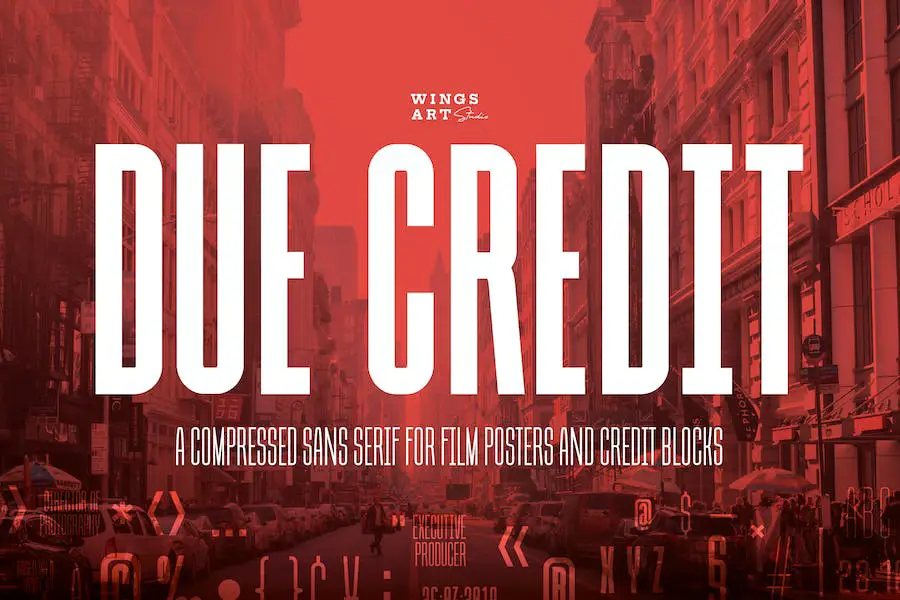
Due Credit ist eine vielseitige Schriftart, die Ihren Designs einen Hauch von Klasse verleihen kann. Es ist in verschiedenen Stärken erhältlich und eignet sich daher ideal für die Erstellung auffälliger Titel und Zitate. Darüber hinaus verfügt es sogar über einen Stil, der von Horror-Genres inspiriert ist und sich perfekt für Halloween-Projekte eignet.
Diese Schriftart wurde speziell für Adobe-Benutzer entwickelt und kann zum Erstellen atemberaubender Typografie in verschiedenen Anwendungen verwendet werden.
Die Auswahl an Stilen und Gewichten stellt sicher, dass Designer die perfekte Option auswählen können, die zur Ästhetik ihres Projekts passt. Die klaren Linien und eleganten Kurven der Schriftart machen sie zu einer ausgezeichneten Wahl für diejenigen, die ihrer Arbeit ein professionelles und elegantes Aussehen verleihen möchten.
Wege
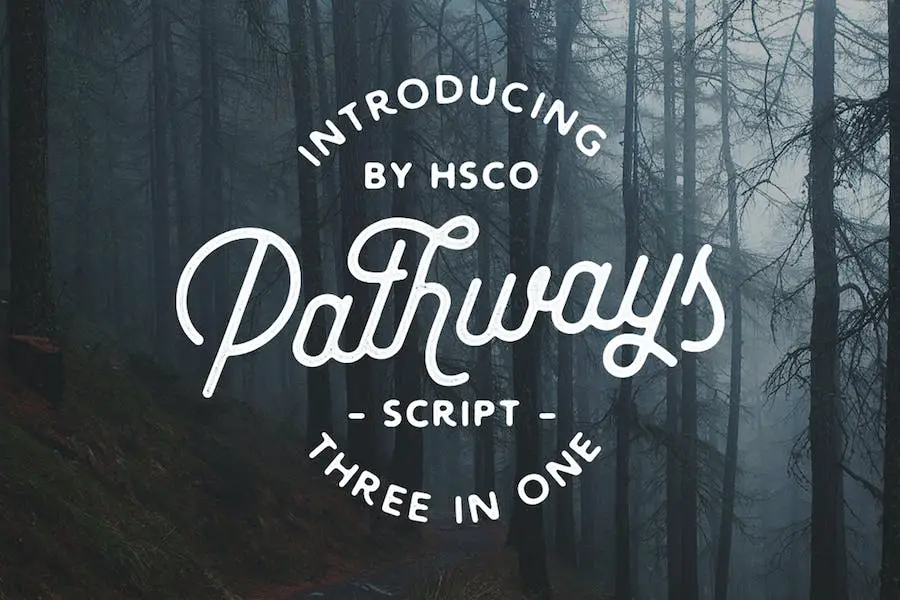
Pathways ist eine vielseitige Schriftart, die in drei verschiedenen Stilen erhältlich ist: kreisförmige Striche, rechteckige Striche und eine grobe Version für eine gedruckte Ästhetik.
Diese Schriftart wurde speziell für Logo- und Etikettendesigner entwickelt und bietet viele alternative Zeichen und Ligaturen, was sie zu einem hervorragenden Werkzeug für Designer macht, die das Design ihrer Projekte verbessern möchten.
Das klare und vielseitige Design von Pathways ist perfekt für alle, die nach Designer-Schriftarten für Canva suchen. Diese Schreibschrift verfügt über einzigartige Funktionen wie alternative Zeichen und Ligaturen, die sie von anderen verfügbaren Schriftarten abheben.
Fallen
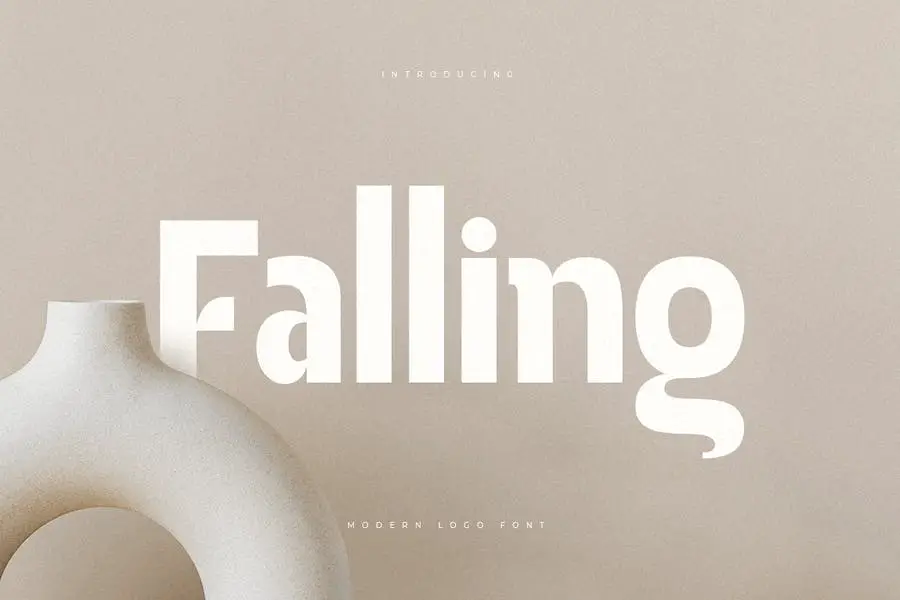
Falling ist eine moderne Schriftart, die einzigartige Branding-Lösungen bietet. Diese Schriftart wurde speziell mit zusätzlichen Ligaturen in einer einzigartigen Form erstellt, die Ihrer Marke einen Mehrwert verleihen kann.
Falling ist ein Muss für jeden, der nach Designer-Schriftarten für Figma sucht. Die zusätzlichen Ligaturen und die einzigartige Form helfen dabei, jedes Designprojekt auf die nächste Stufe zu heben. Wenn Sie Ihrer Marke einen Mehrwert verleihen und gleichzeitig mit den neuesten Designtrends Schritt halten möchten, ist Falling die perfekte Schriftart für Sie.
Stadtrundfahrt
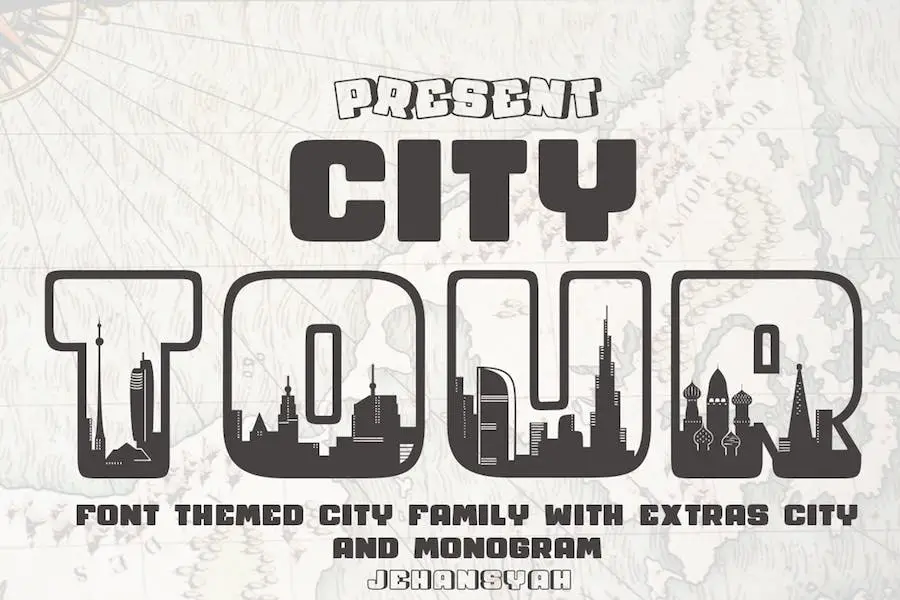
City Tour ist eine einzigartige Schriftart, die verschiedene Schriftarten und Designelemente kombiniert, um eine herausragende alphabetische Darstellung verschiedener Länder zu schaffen. Ziel ist es, Designern die Essenz jedes Landes näherzubringen und zwei Werke in einer Form zu schaffen, die Sie „Wow“ sagen lassen.
Die Schriftfamilie umfasst zehn Zeichenschriften, Extras, Dingbats sowie City TTF- und OTF-Dateien, die einfach als ZIP-Dateien heruntergeladen werden können.
Mit der City Tour-Schriftfamilie können Sie alles nach Ihren Bedürfnissen nutzen, auch die verschiedenen Dateien und Zeichen. Mit Designer-Schriftarten können Sie atemberaubende Designs für Instagram oder jede andere Plattform erstellen.
Meta-Link
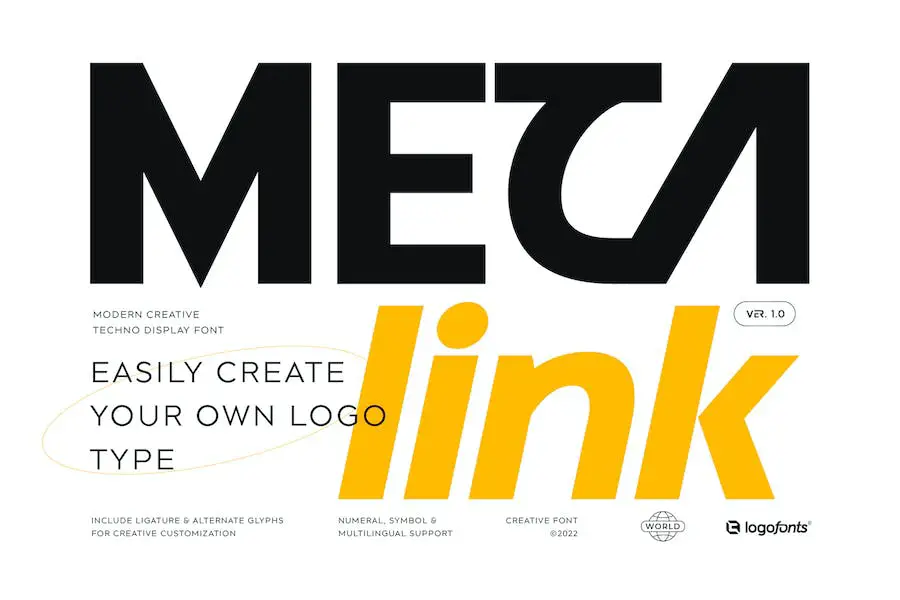
Meta Link ist eine Sans Serif, die die elegante Ästhetik zukünftiger Technologie und Sportarten verkörpern soll. Es eignet sich perfekt zum Erstellen von Logos, Postern, Schlagzeilen, Webdesigns, Magazinen, Verpackungen und Briefpapier.
Diese Schriftart bietet vier Strichstärkenoptionen mit Kursivschrift sowie eine Open-Type-Funktion, die den Zugriff auf eine große Auswahl einzigartiger alternativer Buchstaben und zahlreicher Ligaturen ermöglicht und so die Anpassung Ihrer Designs erleichtert.
Wenn Sie nach Designer-Markenschriftarten suchen, die Ihre Projekte aufwerten, dann sollte Meta Link auf Ihrer Liste stehen. Sie hat eine ausgesprochen futuristische Anmutung, die sie von anderen Schriftarten unterscheidet und Ihren Designs einen modernen Touch verleiht. Dank der vielseitigen Gewichts- und Stiloptionen können Sie eine Vielzahl von Designs kreieren, die auf Ihre Bedürfnisse zugeschnitten sind.
Die Aquabella
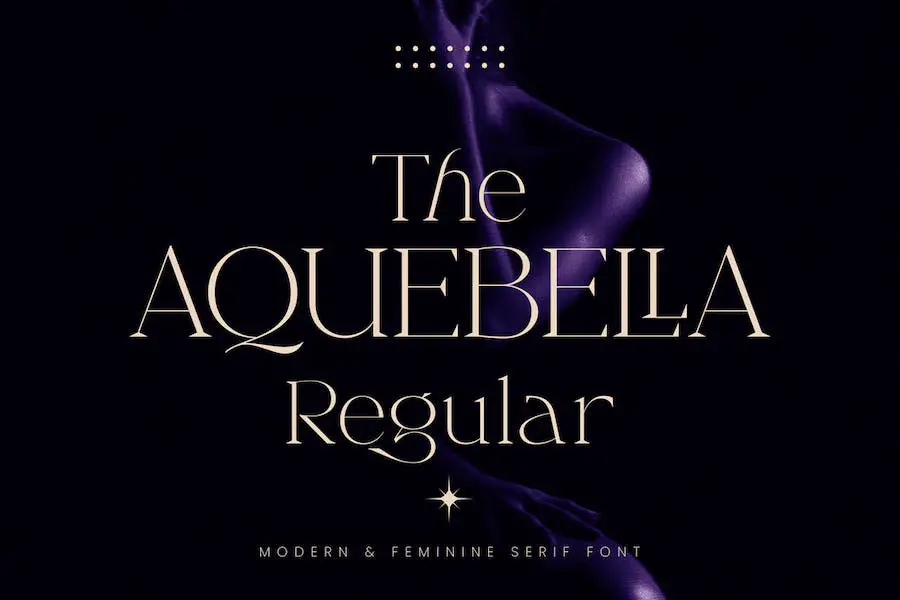
Die Schriftart Aquabella ist eine Serifenschrift, die Grafikdesignern einen einzigartigen und eleganten Stil bietet. Die Schriftart wurde entwickelt, um der Herausforderung gerecht zu werden, eine Serifenschrift zu finden, die sowohl anspruchsvoll als auch einzigartig ist.
Wenn Sie nach einer neuen und einzigartigen Serifenschrift suchen, um Ihre Designs aufzuwerten, ist The Aquabella eine Überlegung wert. Ihr eleganter Stil und ihre Lesbarkeit machen sie zu einer herausragenden Wahl unter den Designerschriften für Fotografen.
Loistave
Loistave ist eine atemberaubende zweiseitige Serifenschrift, die Raffinesse und Modernismus ausstrahlt. Mit seinen sanften Kurven und dem symmetrischen Design ist es die perfekte Wahl für jedes Mode-Branding oder redaktionelle Projekt. Diese Schriftart besitzt eine zarte Eleganz, die jedes Bild zum Leben erwecken kann.
Insgesamt ist Loistave eine Bildschrift der Spitzenklasse, die sowohl Stil als auch Funktionalität bietet. Die sanften Kurven und ausgewogenen Serifen bringen Ihre Designs auf die nächste Ebene und machen diese Schriftart zu einem Muss für jeden Designer.
Designer-Schriftartenpaket
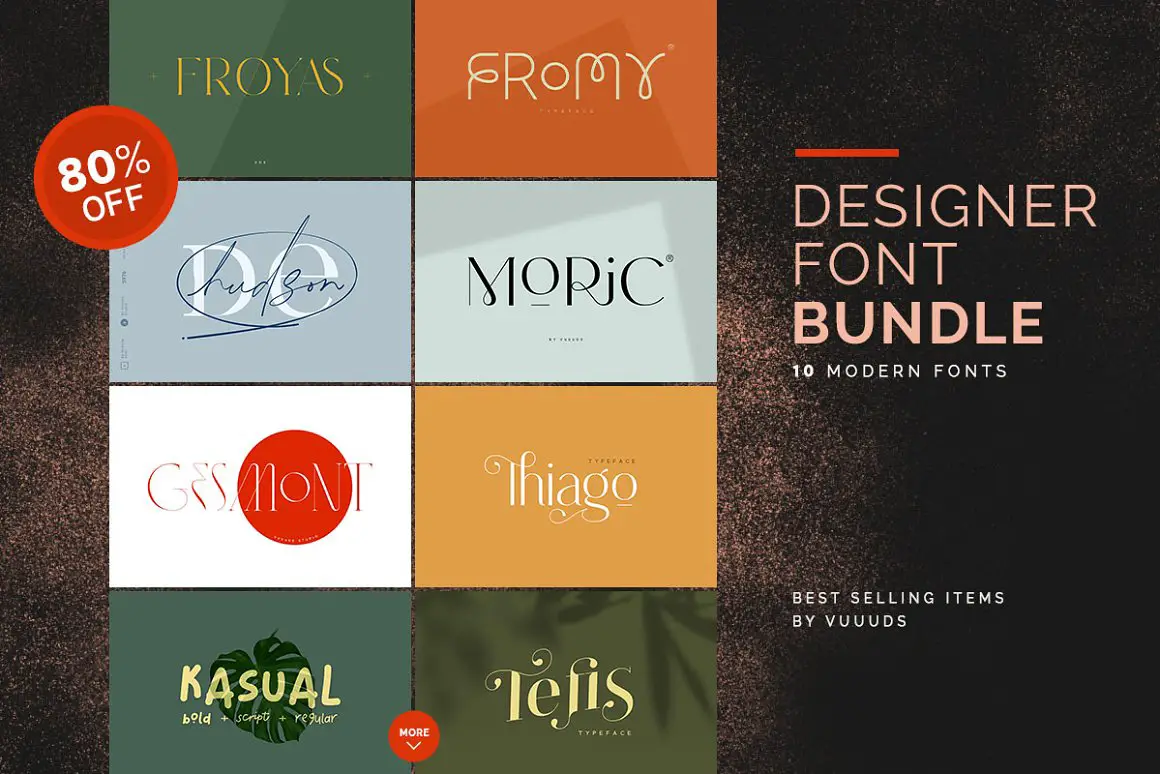
Das Designer Font Bundle ist ein Muss für jeden Grafikdesigner, der das Design seiner Projekte verbessern möchte. Dieses Paket geht über reine Schriftarten im Serifenstil hinaus und umfasst moderne Skriptschriftarten, sodass Sie mehr Optionen zum Auswählen und Experimentieren haben.
Wenn Sie Ihre Designprojekte auf die nächste Stufe heben möchten, ist das Designer Font Bundle eine ausgezeichnete Investition.
Mit der vielseitigen Auswahl an Schriftarten und der benutzerfreundlichen Oberfläche können Sie im Handumdrehen atemberaubende Designs erstellen. Und mit der Möglichkeit, Google Designer-Schriftarten zu verwenden, stehen Ihnen noch mehr Inspirationen zur Verfügung.
Minimalistisches Schriftartenpaket
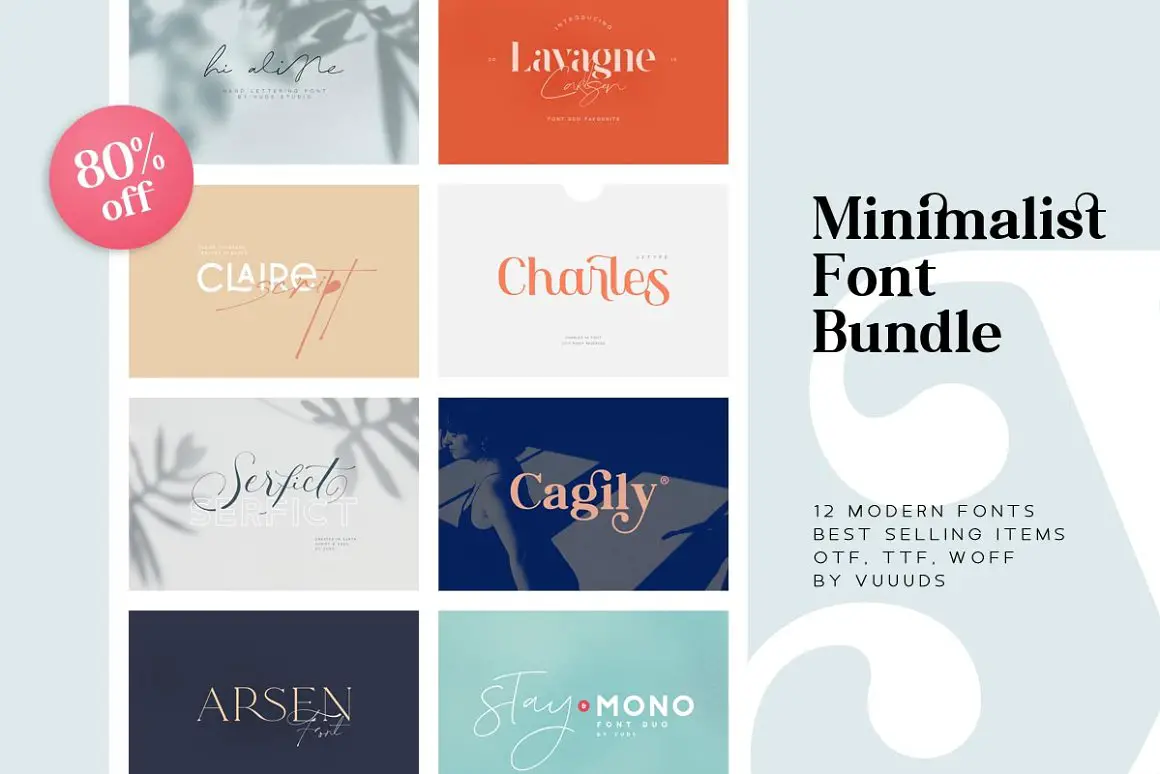
Das Minimalist Font Bundle ist eine ausgezeichnete Wahl für Grafikdesigner, die nach vielseitigen und eleganten Designerschriftarten für Word suchen. Mit insgesamt 27 Schriftarten, die in diesem Paket enthalten sind, haben Designer eine große Auswahl an Optionen.
Das Minimalist Font Bundle ist eine außergewöhnliche Ressource für Designer, die nach einer breiten Palette an Designerschriftarten für Word suchen. Dieses Paket bietet Vielseitigkeit, Eleganz und individuelle Anpassungsmöglichkeiten und ist somit die ideale Wahl für jedes Designprojekt.
Designer-Dingbats
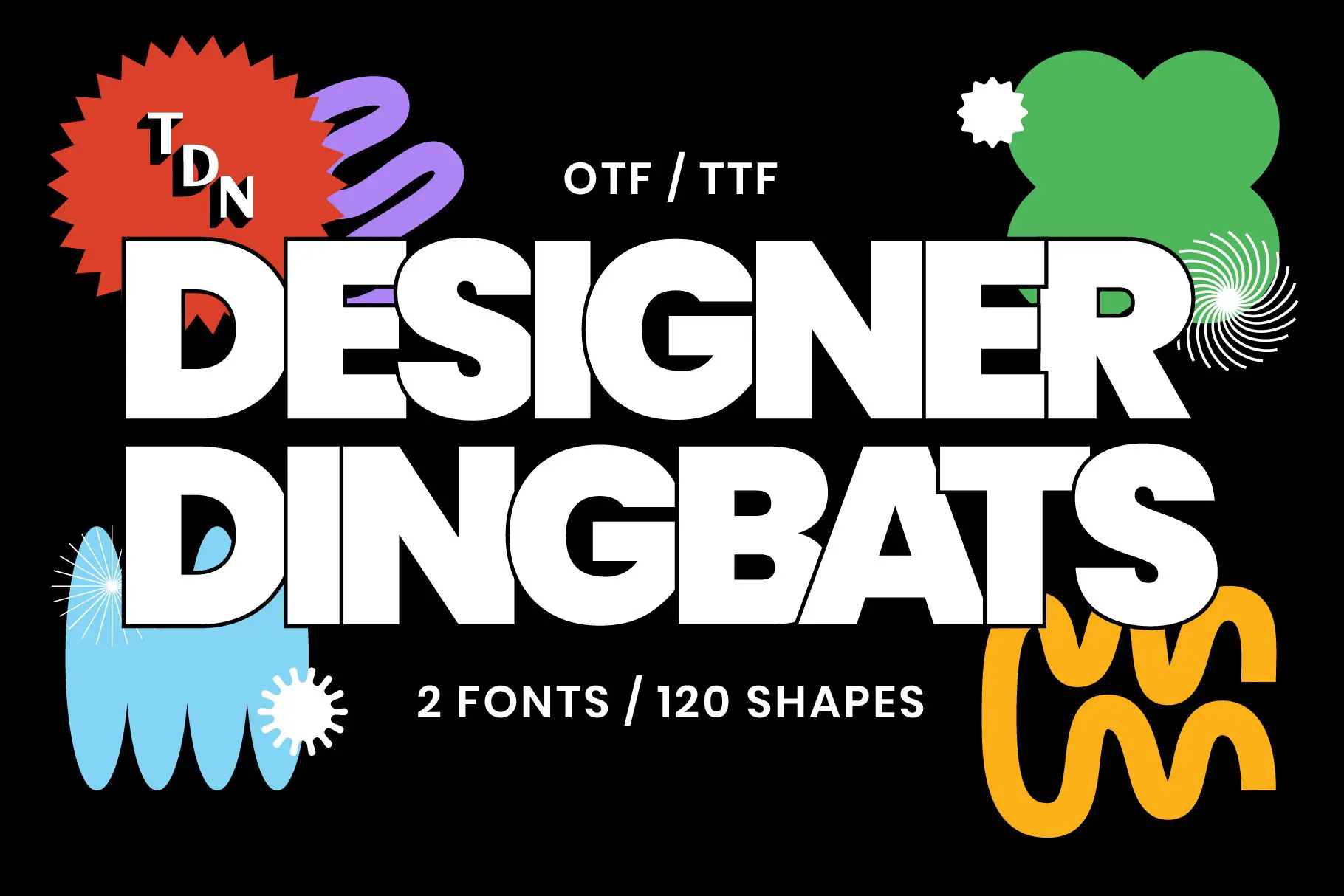
Designer Dingbats ist eine unverzichtbare Ergänzung Ihres Design-Toolkits! Mit 120 neuen Formen zur Auswahl können Sie Ihre Designs aufwerten und auf die nächste Ebene bringen.
Dieses Produkt bietet eine umfangreiche Auswahl an Mustern, die auf mehreren Plattformen wie Branding, Verpackung, Social Media und mehr verwendet werden können. Sie können auch Designer-Schriftarten für Circuit in Betracht ziehen.
San Diego
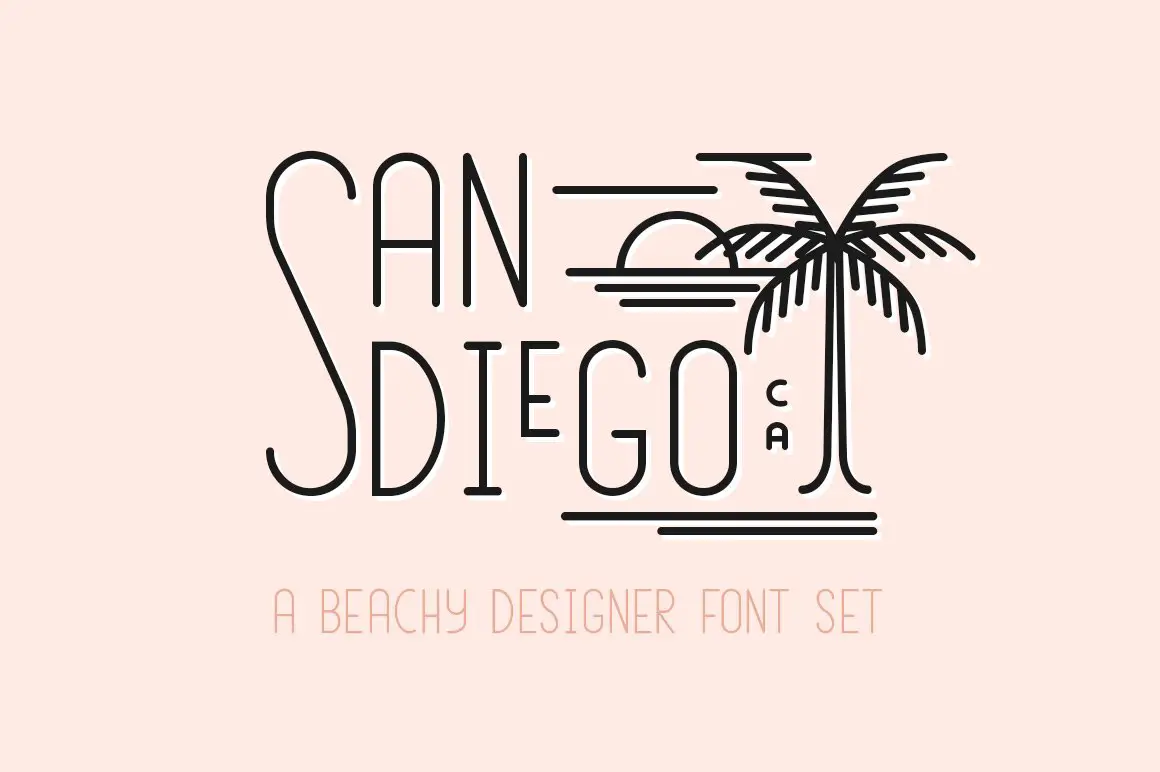
San Diego ist ein Designer-Schriftsatz, der einen Vintage-Look und -Feeling bietet und sich daher hervorragend für die Erstellung von Logos und Designs im Retro-Stil eignet. Egal, ob Sie an Einladungen, Beschilderungen oder einem anderen Projekt arbeiten, der Vier-Schriftsatz von San Diego kann Ihnen dabei helfen, Ihre Arbeit zu vereinfachen und schöne Ergebnisse zu erzielen.
Insgesamt ist San Diego eine hervorragende Wahl für alle, die ein vielseitiges und optisch ansprechendes Design-Schriftset suchen.
Sein Vintage-Stil und die eleganten Kurven machen es zur ersten Wahl für alle, die ihren Designs einen Hauch von Old-School-Charme verleihen möchten. Wenn Sie auf der Suche nach Designer-Schriftarten für Tätowierungen oder andere Projekte sind, schauen Sie sich unbedingt San Diego an.
Nirotica
Nirotica ist eine Serifenschrift, die sich perfekt für Grafikdesigner eignet, die ihren Projekten einen Hauch von Luxus und Stil verleihen möchten.
Der moderne Stil von Nirotica macht es vielseitig und für eine Vielzahl von Zwecken geeignet. Die Schriftart funktioniert sowohl in gedruckten als auch in digitalen Formaten gut und ihre klaren Linien und eleganten Kurven machen sie leicht lesbar und behalten dennoch ein unverwechselbares Flair.
Insgesamt ist Nirotica eine großartige Schriftart für Grafikdesigner, die ihrer Arbeit einen zusätzlichen Hauch von Luxus verleihen möchten.
Bonky Serif
Bonky Serif ist eine Vintage-Schriftart im modernen Stil, die sich perfekt für Designer eignet, die ihren Projekten einen Hauch von Raffinesse verleihen möchten. Diese Schriftart wurde mit größter Genauigkeit erstellt und verfügt über alternative Zeichen und Ligaturen, mit denen Sie einzigartige Designs erstellen können.
Wenn Sie moderne Designer-Schriftarten benötigen, die Ihren Projekten helfen, Wirkung zu erzielen, ist Bonky Serif auf jeden Fall eine Überlegung wert.
Der Vintage-Look und die modernen Motive machen es zu einer vielseitigen Wahl für jedes Projekt. Probieren Sie es noch heute aus und sehen Sie, wie es Ihre Designs auf die nächste Stufe heben kann.
Zigarre
Cigra ist eine außergewöhnliche Displayschrift, die eine Hommage an die moderne Typografie der Modewelt darstellt. Mit anmutigen Kurven und einzigartigen Formen ist es die perfekte Wahl zum Erstellen von Überschriften und Logos oder zum Verleihen von Flair an Hochzeitseinladungen.
Cigra strahlt Eleganz aus und ist eine stilvolle Schriftart, die garantiert jedem ins Auge fällt.
Seine einzigartigen Kurven und eleganten Formen machen es zu einer hervorragenden Option für alle, die ihren Designs einen Hauch von Klasse verleihen möchten. Anspruchsvoller und stilvoller können Schriftarten für Designer nicht sein!
Beste kostenlose Designer-Schriftarten
Wenn Sie als Designer Ihrer Sammlung frische, hochwertige Schriftarten hinzufügen möchten, ohne Ihr Budget zu sprengen, dann ist dieser Abschnitt genau das Richtige für Sie. Werfen Sie einen Blick auf unsere kuratierte Liste der besten verfügbaren kostenlosen Designer-Schriftarten und werten Sie Ihre Designprojekte noch heute auf.
Designer
Designer von Belina Studio ist eine Schriftart, die für den persönlichen Gebrauch kostenlos ist. Es hat ein modernes und klares Aussehen und eignet sich daher perfekt für professionelle Grafikdesigns oder persönliche Projekte. Die Schriftart ist sowohl in Groß- als auch in Kleinbuchstaben verfügbar und bietet so Flexibilität bei der Verwendung.
Kreativer Designer
Creative Designer ist eine Schriftart, die von Jetsmax Studio für Designer erstellt wurde. Diese Schriftart ist perfekt für Designer, die nach einer Schriftart suchen, die das Design ihrer Projekte verbessert.
Die Schriftart „Creative Designer“ ist kostenlos erhältlich, was sie zu einer ausgezeichneten Wahl für diejenigen macht, die gerade erst anfangen und nicht viel Budget für Schriftarten haben.
Cottage-Designer
Cottage Designer von Micro Andi ist eine neue Schriftart, die in der Welt des Grafikdesigns für Aufsehen gesorgt hat. Diese stilvolle und elegante Schriftart kann von Designern verwendet werden, um das allgemeine Erscheinungsbild ihrer Projekte zu verbessern.
Süß wie Honig
Sweet Like Honey, erstellt von Jimtype Studio, ist eine kostenlose, nichtkommerzielle Schriftart, die auf jedem Gerät verwendet werden kann, einschließlich PC, Mac, Linux, iOS und Android. Diese Schriftart hat einen verspielten und dennoch eleganten Stil und ist daher eine ausgezeichnete Wahl für Designer, die ihren Projekten einen Hauch von Raffinesse verleihen möchten.
Irendy
Irendy ist eine innovative Schriftart, die Ihren Designs eine verspielte Note verleiht. Die Schriftfamilie verfügt über eine reguläre Unterfamilie, die allen Arten von Projekten ein einheitliches Erscheinungsbild verleiht. Es ist wichtig zu beachten, dass Irendy nur für persönliche Projekte verwendet werden sollte.
Der Einbruch der Dunkelheit
„Nightfall“ von Skinny Type ist eine moderne Schreibschrift mit einer beeindruckenden Auswahl an kräftigen, eleganten und Vintage-Schwungfarben. Durch die PUA-Kodierung wird Ihnen der Zugriff auf die verfügbaren Glyphen und Schwünge erleichtert.
Mitglieder der Gesellschaft
Society Members von Niskala Huruf ist eine Schriftart, die nur für persönliche Zwecke verwendet werden darf. Es handelt sich um eine stilvolle und elegante Schriftart, die das Design verschiedener Projekte verbessern kann. Die Schriftart hat ein einzigartiges und anspruchsvolles Aussehen und eignet sich perfekt, um jedem Design einen Hauch von Klasse zu verleihen.
Häufig gestellte Fragen
Unter Designer-Schriftarten versteht man einzigartige und kreative Schriftarten, die speziell dafür entwickelt wurden, die visuelle Attraktivität eines Textes zu verbessern, ihn hervorzuheben und eine bestimmte Stimmung oder Persönlichkeit zu vermitteln.
Die Verwendung von Designer-Schriftarten kann dazu beitragen, dass Ihr Text professioneller und ansprechender aussieht und Ihrem Publikum einen bestimmten Ton oder eine bestimmte Botschaft vermittelt. Es kann Ihren Text auch von anderen abheben und ihn einprägsamer machen.
Bei der Auswahl einer Designerschrift ist es wichtig, den Ton und die Botschaft Ihres Projekts zu berücksichtigen. Serifenschriften sind traditioneller und professioneller, während serifenlose Schriftarten modern und klar sind. Stellen Sie außerdem sicher, dass die Schriftart in verschiedenen Größen gut lesbar und gut lesbar ist.
Abschluss
Abschließend haben wir die 21 besten Designer-Schriftarten besprochen, die Grafikdesigner in ihren Projekten verwenden können. Diese Schriftarten können dazu beitragen, das Gesamtdesign zu verbessern und Ihre Arbeit hervorzuheben. Mit der richtigen Schriftartenwahl können Sie Ihre Designs auf ein neues Niveau heben.